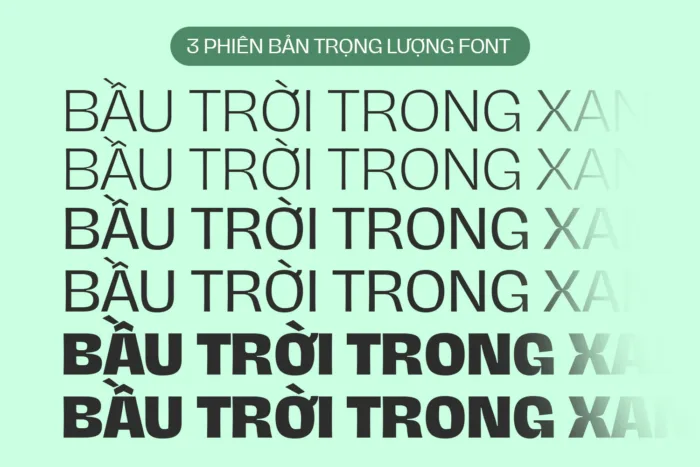
Bộ font DVN Hagrid Việt hóa – Nét chữ thanh mãnh tinh tế, kiểu dấu thế hệ mới mang xu hướng hiện đại (3 Style)
DVN Hagrid Việt hóa là bộ font mang phong cách hiện đại với nét chữ thanh mảnh và tinh tế. Thiết kế tối giản nhưng đầy cá tính, phù hợp cho cả tiêu đề và nội dung văn bản. Điểm nổi bật của font này là kiểu dấu thế hệ mới, được tinh chỉnh để hài hòa với các ký tự, tạo sự cân bằng về thị giác và giúp văn bản trông gọn gàng, dễ đọc.
DVN Hagrid mang đến sự linh hoạt trong thiết kế, phù hợp với nhiều lĩnh vực như branding, in ấn, giao diện web, và thiết kế đồ họa. Kiểu chữ mang hơi hướng tối giản nhưng không đơn điệu, kết hợp giữa nét thanh lịch và sự vững chãi, giúp tăng cường tính thẩm mỹ cho các dự án sáng tạo. Đây là lựa chọn lý tưởng cho những ai đang tìm kiếm một font chữ hiện đại, tinh tế và phù hợp với xu hướng thiết kế đương đại.
Phiên bản Việt hóa bao gồm 3 Style: Light, Regular và Extra Bold